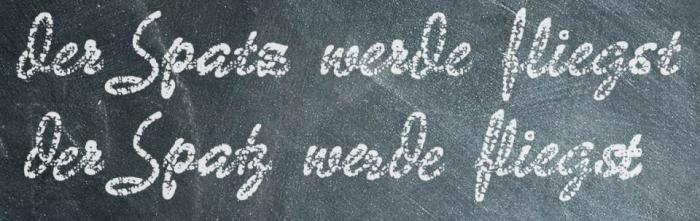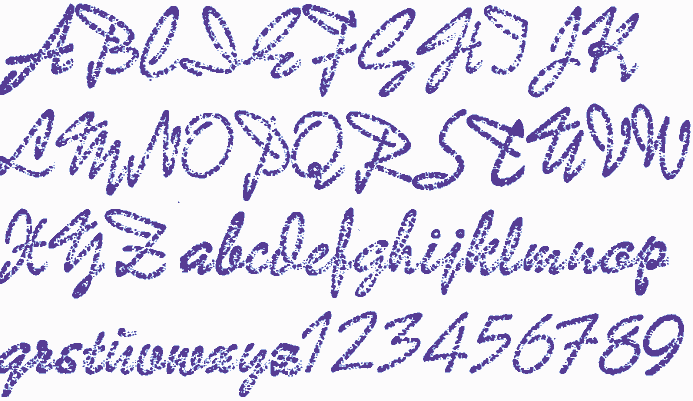
Font, der nach Tafel-Kreide-Schrift aussieht
Kennt jemand Fonts oder Tools, mit der man relativ authentisch Kreide-Schrift auf einer Tafel erzeugen kann? Danke vorab für die Hilfe!
Wie authentisch muss es denn sein? Tafelkreideoptik für, sagen wir, eine Überschrift, oder Fotorealistisch in ein Foto eingebaut ...?
Beides wäre nicht schlecht. Einmal Font für Plakat, aber auch ein Tool mit dem ich z.B. das Logo in Kreide-Optik darstellen könnte. Offe für alles ...
Hier gibt’s die "Tafelkreide". Nur Versalien, aber sehr umfangreich.
Habe auch mal ne Mail an den FontShop geschickt und die zwei
hier noch als Antwort bekommen (um noch weitere in die Runde zu schmeißen):
-Tafelkreide (allerdings nur Versalien)
-John Handy
Dann macht doch mal ’ne Liste fürs Wiki ...  :hammer:
Ob’s die digitalisiert gibt? Ich kann ja mal recherchieren …
Andere Frage: Die Schriften, die hier im Thread genannt werden, sind von recht unterschiedlicher Qualität. Und in einem Fall – der hübschen Arid, die Pachulke vorgeschlagen hat – handelt es sich trotz der rauen Struktur erkennbar um eine Pinselschrift (ich vermute einen Filzstift mit pinselförmiger Filzspitze) und nicht um eine Kreideschrift. Wie genau wollen wir es damit nehmen? Für den Anfang habe ich jetzt mal Sammy, Pedell, Lipstick,  Furu und Jacqueline ins Wiki eingepflegt (die letzten beiden muss Ralf mir noch freischalten). Welche der übrigen Vorschläge hier aus dem Thread sollten wir noch aufnehmen? Und welche aus Qualitätsgründen vielleicht eher nicht?